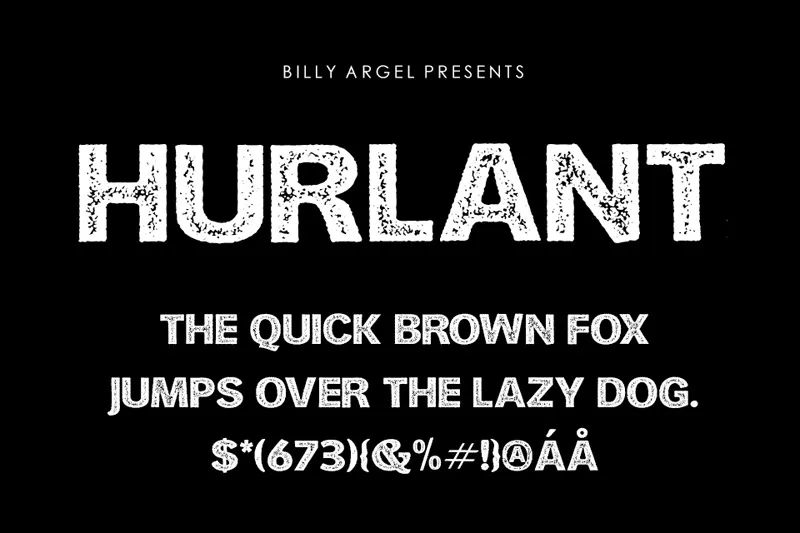
Hurlant Font – Download Grátis
A Hurlant Font é uma opção perfeita para projetos que precisam de um ar elegante e moderno, sem deixar de lado sua personalidade vintage suave. Esta fonte do display é o tipo certo para aqueles desejando dar um toque único em seus designs digitais. Com apenas dois estilos, regular e itálico, a Hurlant abraça uma aparência clara e moderna que contrasta perfeitamente com sua elegância vintage. Feita inteiramente à mão pelos artistas da 99designs, esta fonte oferece um único toque de originalidade que vai revolucionar seu visual. Seja para criar cartazes impactantes ou textos para o site do seu novo negócio, a Hurlant tem tudo aquilo que você precisa para dar ao seu design uma cara diferente e mais sofisticada. Com sua disposição fácil de usar e dois estilos prontos para uso, é ótima para quem quer tornar seus projetos ainda mais belos e simples, sem sacrificar estilo ou personalidade. Não perca tempo e dê vida à sua marca com a Hurlant Font.